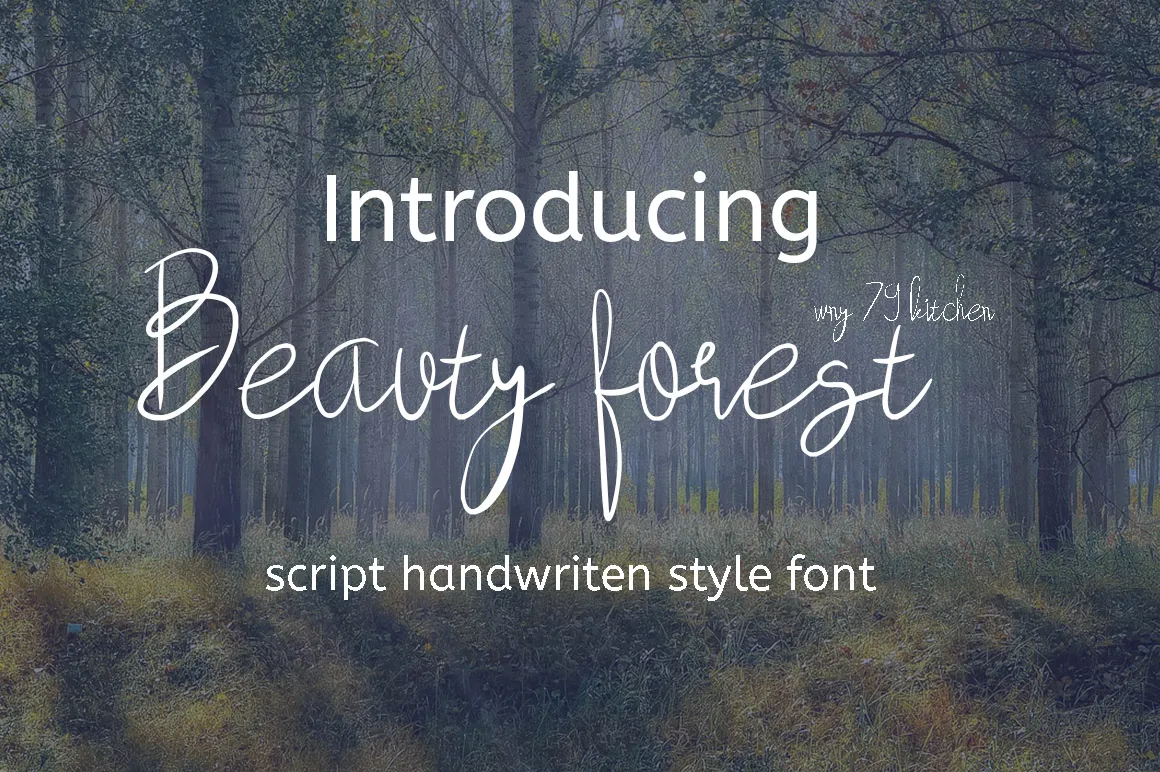
Beauty Forest Script Font – Download Grátis
A Beauty Forest Script Font é uma elegante fonte escrita a mão que transmite paz e beleza. Perfeita para uma ampla gama de projetos, esta fonte foi criada para oferecer um estilo autêntico que pode dar seu trabalho ou produto um toque único e singular. Com o designer wny79, você poderá adicionar um ar distinto a qualquer projeto, seja ele uma marca, um site personalizado, cartazes de eventos ou até mesmo letras no livro impresso. Essa fonte escrita a mão oferece flexibilidade para se adaptar a diversos estilos, permitindo que seu trabalho ou produto fique ainda mais profissional e inovador. Seja qual for o projeto, Beauty Forest Script Font traz uma sensação autêntica e de paz à sua criação.